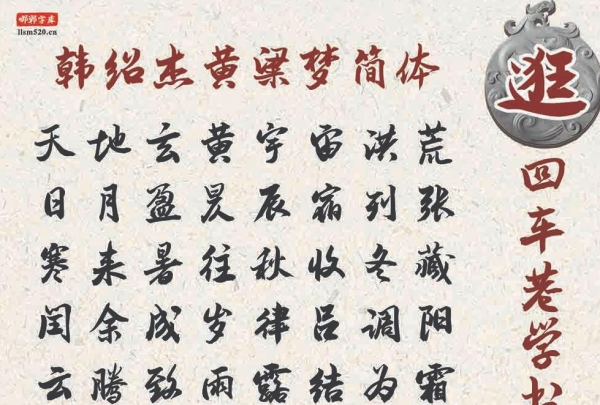
韓紹杰黃粱夢(mèng)簡(jiǎn)體以邯鄲體創(chuàng)始人韓紹杰老師書(shū)寫(xiě)的毛筆字創(chuàng)作而成,韓老師習(xí)字四十余載,融會(huì)米芾、蘇體及行楷,自成風(fēng)格?,F(xiàn)將字體數(shù)字化,服務(wù)于全國(guó)網(wǎng)民大眾,讓邯鄲文化得以流傳。該字體用筆靈動(dòng)多變,爽利中見(jiàn)力量,飛白勁健而又沉著,起收筆、提按、 頓挫隨心所欲,姿態(tài)飛動(dòng),中側(cè)鋒并用,變化莫測(cè),"風(fēng)檣陣馬 ,沉著痛快”,自稱"八面出鋒”,體勢(shì)多欹側(cè),章法疏密相間。屬于書(shū)法大字榜書(shū)范疇,適用于書(shū)籍的封面,以及品牌廣告和產(chǎn)品包裝設(shè)計(jì)尤其適合做古籍牌匾用字。